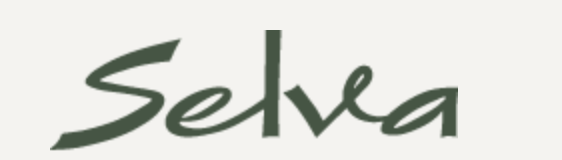
Schrift gesucht! Brauche bitte Hilfe!
es handelt sich um ein Logo (Hotel im alpinen Raum)
... Hm, kommt mir aber so vor, als sei ich letztens über so einen ähnlichen Font gestolpert ... ich grüble mal, vielleicht hilft's (oder der bertel ist schneller).
Wenn man wüsste, welches Hotel das ist, könnte man sich auf die Suche machen. Ich vermute aber auch eher ein gestaltetes Logo als einen Font.
Das lässt sich nicht googeln; "selva" heißt so viel wie Wald, wenn ich mich recht erinnere – da könnte man gleich ein Hotel "Zur Post" suchen.
tippi toppi danke für die Hilfe, ich habs einfach nachkalkuliert und den Zusatz "Chalet" im selben Stil angefertigt
p.s. der Kunde findet die Originaldatei nichtmehr ;-)
Weißt du denn, ob das ursprünglich auf einem Font basiert oder ob das gezeichnet wurde?